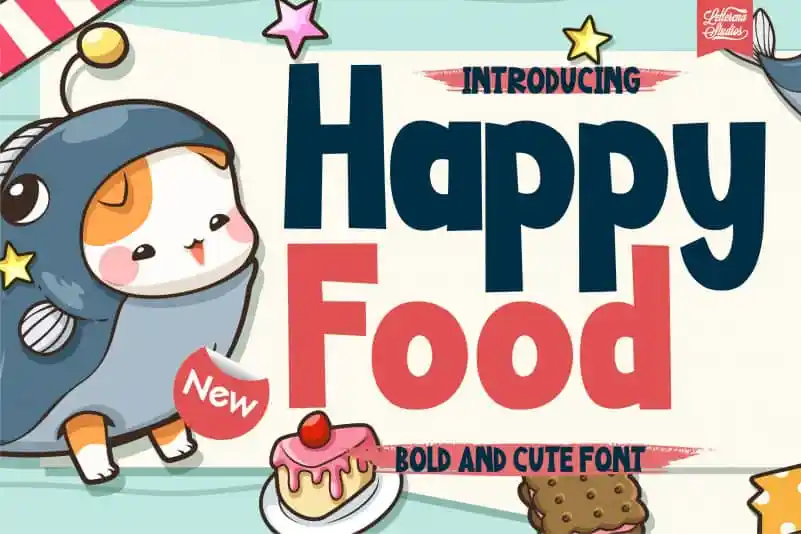
A Happy Food Display Font é uma escolha perfeita para quem busca um ar descontraído e alegre em seus projetos visuais. Seu estilo casual e moderno torna essa fonte perfeitamente adaptável a diversos tipos de designs, do design gráfico até o marketing digital. Com sua aparência vibrante e encantadora, é uma escolha ideal para quando você quer expressar leveza e bom humor em seus projetos. Experimente adicioná-la a seu próximo projeto e descubra como ela pode marcar a diferença na criação de designs únicos e atraentes que se destacam do resto da concorrência.